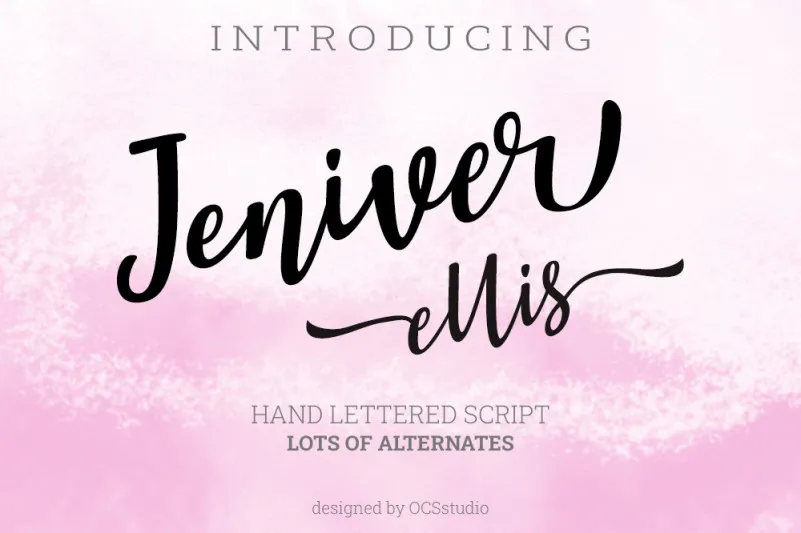
Jeniver Ellis Script Font – Download Grátis
Através do processo delicado de desenho realizado com uma ferramenta de pincel, nasceu Jeniver Ellis Script Font. Esta fonte é perfeita para aquelas necessidades que exigem um toque delicado e autêntico, como eventos festivos, convites de casamento, carteirinhas de acompanhante, números das mesas, citações, logotipos, banners e embalagens personalizadas. Seu design tem uma estrutura limpa e simples que evoca a essência dos desenhos do ballet, criando um padrão visual único para se destacar em sua próxima criação gráfica. Jeniver Ellis Script Font é perfeito para expressar nuances delicadas de forma elegante e eficaz, tornando-o uma opção versátil para diversos usos de design.